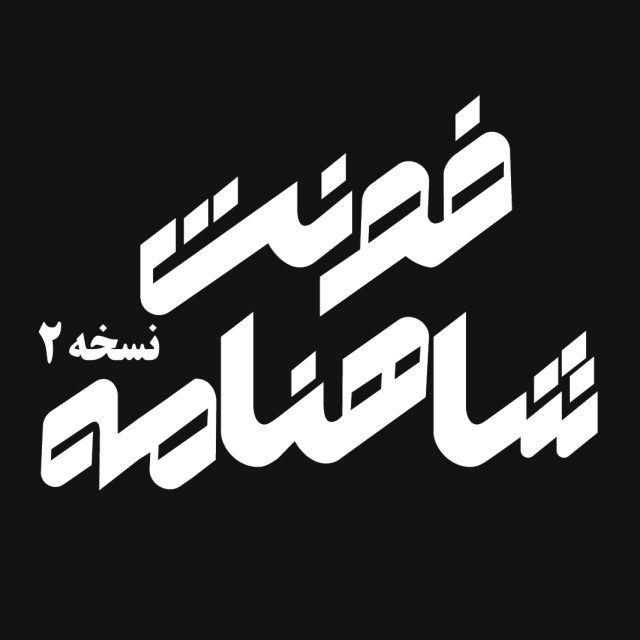
فونت ویژه ای که در این پست می خواهیم برای شما معرفی کنیم فونت تایپوگرافی شاهنامه می باشد که در سایت دیاکوگرافیک تهیه شده است و یک فونت تمام و کمال برای طراحی یک لوگو تایپ فوق حرفه ای در تک وزن بولد می باشد کاربرد فونت شاهنامه در بنر های چلنیوم،تابلوها،تبلیغات محیطی و به ویژه طراحی لوگوتایپ های فارسی می باشد در ادامه پیشنمایش های فونت شاهنامه شمارا شگفت زده خواهد کرد.
فونت شاهنامه با یک استایل منحصر به فرد و کاملا متفاوت از فونت های حیطه تایپوگرافی طراحی شده است و از این جهت طرح های شما را متفاوت تر خواهد کرد.پیشنهاد میکنیم از این فونت فقط در طراحی لوگو،تایپوگرافی و طراحی پوستر و یا در تیتر ها استفاده کنید. این فونت مناسب تایپ های طولانی کتابی نمی باشد و فقط برای استفاده در طراحی تابلوها،لوگوتایپ ها،متن های برجسته از این فونت استفاده کنید.
- تغییرات نقطه ها و اصلاح حروف در نسخه دوم (جدید)
- مناسب برای طراحی لوگو تایپ های حرفه ای
برخی تایپ هایی که با این فونت انجام شده است: